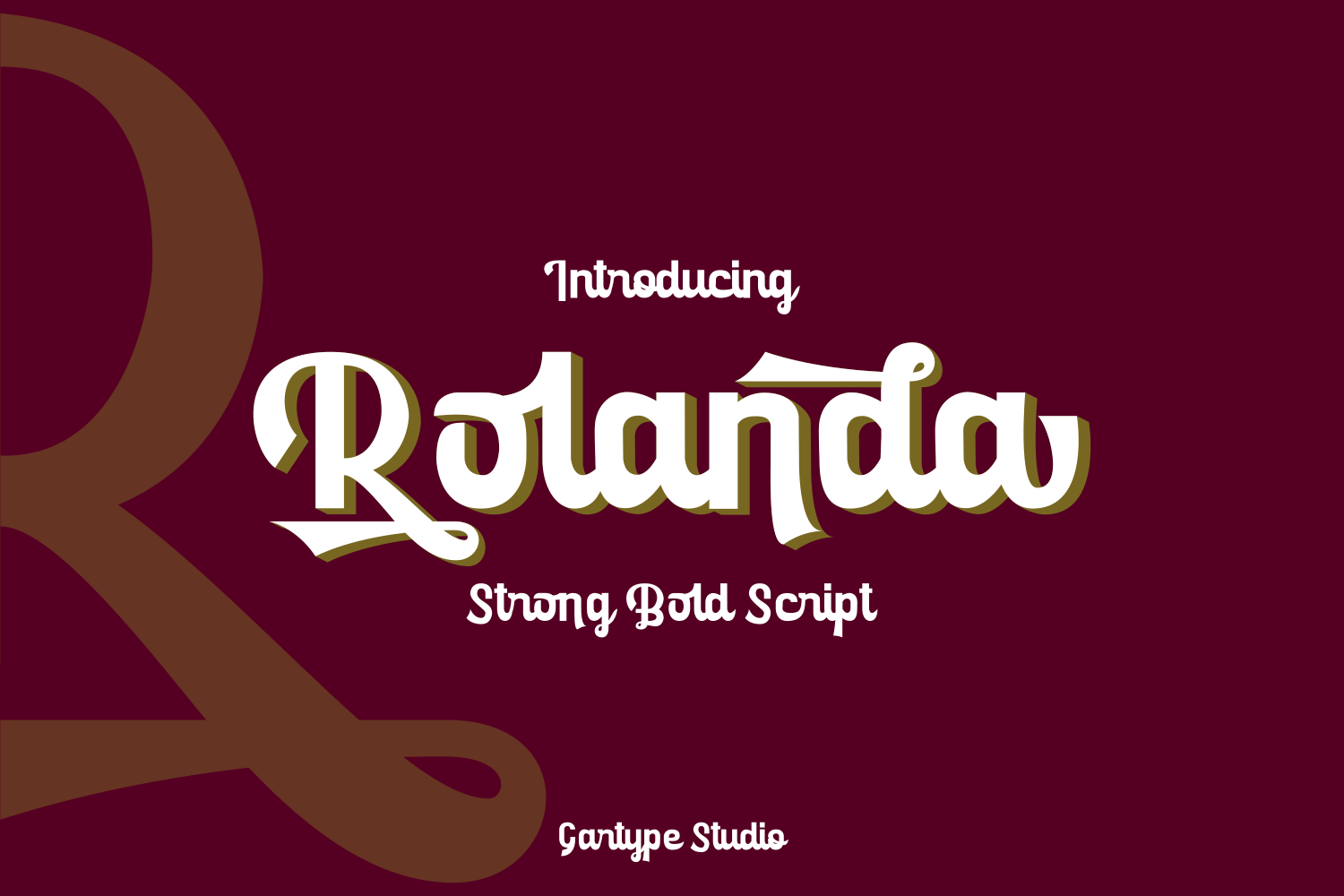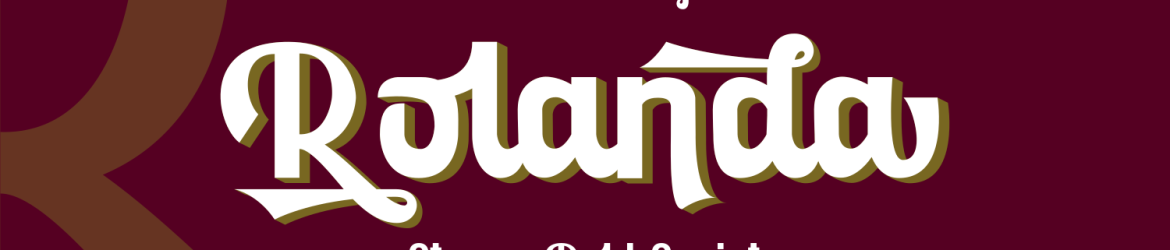
A Rolanda é uma mistura única de fontes robusta, negrito e script, inspirada nos belos traços vintage das tipografias anteriores. Esta font apresenta um estilo elegante e moderno que vai desde criar logotipos até a criação de etiquetas, marcações, flyers, títulos, cartazes e camisetas. Ela é perfeita para quem busca algo único para seus projetos, tornando-a uma escolha ótima tanto para designers profissionais quanto para aqueles iniciantes que procuram um novo desafio. Composta de linhas fortes e um estilo elegante, a Rolanda é uma fonte ideal para qualquer aplicação visual onde desejará adicionar um toque personalizado ao seu design.
Designer: Gartype Studio